Reseña de Refont.ai: la forma simple de crear tipografías con estilo
¿Buscas dar un toque personal a tus publicaciones en redes sociales o a tu branding? Refont.ai promete una forma fácil de generar hermosas tipografías y efectos de texto sin habilidades de diseño. Decidí explorar si esta herramienta gratuita cumple con su promesa. Si te interesa crear caligrafía, firmas o textos elegantes sin esfuerzo, continúa leyendo para una reseña honesta. Probé sus funciones para comprobar cuán fácil de usar y cuán efectiva es realmente.
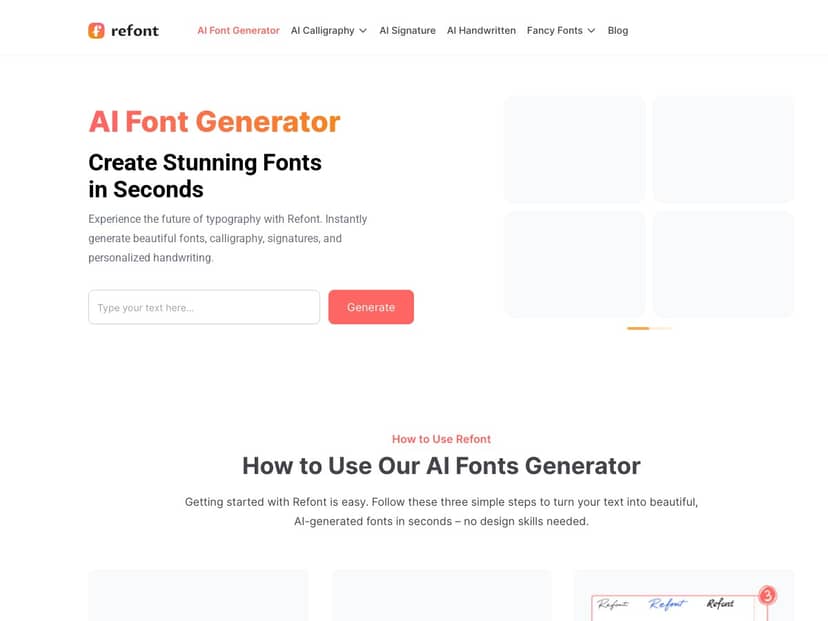
Refont.Ai
Reseña de Refont.ai
Como alguien a quien le gusta experimentar con tipografías, pero no es un diseñador profesional, encontré Refont.ai sorprendentemente sencillo. La interfaz es limpia y simple, con vistas previas instantáneas de tu texto con estilo. Me encantó lo rápido que podía convertir un texto simple en una caligrafía elegante o en tipografías con estilo para redes sociales. La salida se genera principalmente como imágenes con fondos transparentes, perfectas para compartir rápidamente o para visuales de marca. Aunque no se pueden descargar archivos de fuente completos como .ttf o .otf, la capacidad de generar texto estilizado de alta calidad al instante lo hace muy práctico para uso digital. Aprecié que no fuera necesario registrarse, lo que hace que el proceso sea totalmente libre de complicaciones.
Características clave
• AI Calligraphy Generator genera estilos de escritura a mano elegantes a partir de tu texto
• AI Signature Generator ayuda a crear firmas digitales personalizadas
• AI Handwritten Font Generator genera escritura manuscrita realista y de aspecto natural
• Fancy Font Generator añade estilo a las biografías y subtítulos de redes sociales
• Calligraphy Logo Maker permite diseños de logotipos con elementos de caligrafía
• Imágenes descargables de alta resolución con fondos transparentes
• Ventajas y Desventajas
Ventajas
• Muy fácil de usar, con una interfaz simple
• Crea imágenes de texto con estilo al instante
• Ideal para redes sociales, branding y contenido visual rápido
• Soporta varios idiomas, incluido el chino
• Contras
• Opciones limitadas para una personalización profunda o ediciones
Conclusión
En resumen, Refont.ai es una excelente herramienta gratuita para crear efectos de texto llamativos sin complicaciones. Aunque no ofrece fuentes instalables, su facilidad de uso y resultados inmediatos lo convierten en una opción perfecta para publicaciones en redes sociales, visuales de marca y proyectos de diseño rápidos. Si necesitas un texto bellamente diseñado en segundos, Refont.ai definitivamente vale la pena probarlo.